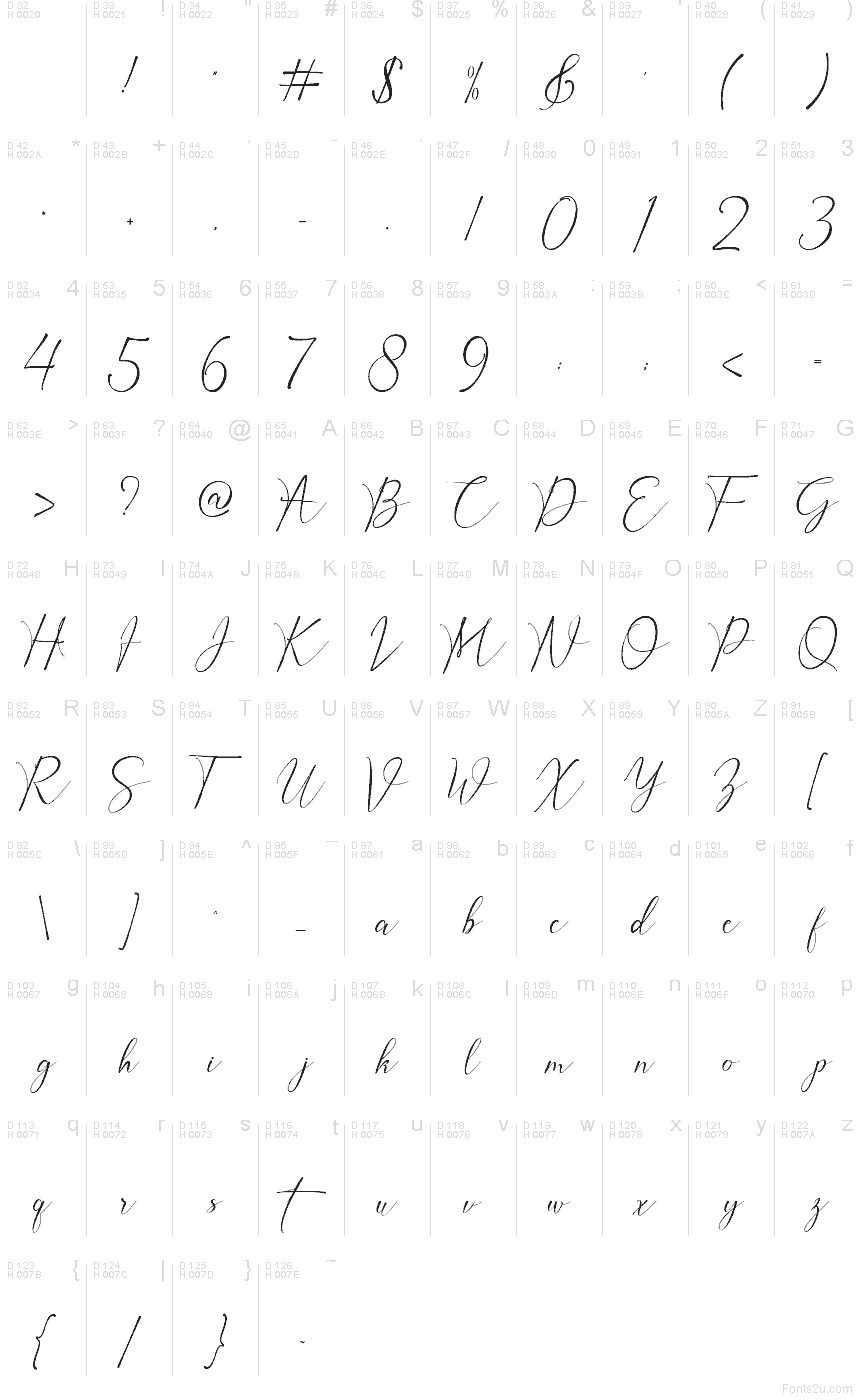
Inter Signature ist eine kostenlose Signatur-Schrift mit schlanken, kontrastreichen Strichen und einer ausgeprägt persönlichen Note. Ihre hohen Schlaufen, langen Querabstriche und leicht verbundenen Buchstaben erzeugen eine luftige Silhouette, deren schnelle Stiftbewegungen elegant statt steif formell wirken.
Eine Modekampagne ist ein überzeugender Rahmen für diesen Schriftzug, besonders auf Lookbooks und Redaktionscovern, wo ein handgeschriebener Akzent die Signatur eines Designers widerspiegeln kann. Sie kann auch die Identität einer Kosmetikmarke oder einer Boutique-Produktlinie prägen und einen Namen in ein wiedererkennbares Markenelement im Autogramm-Stil verwandeln.
Die Merkmale umfassen:
- Anfangs- und Endschwünge
- Ligaturen